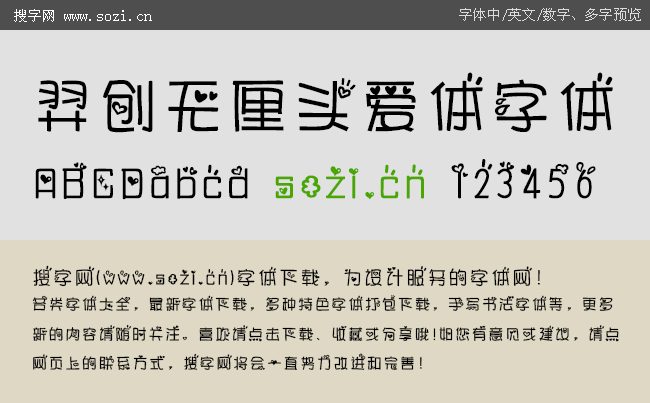
羿創(chuàng)無厘頭愛體字體
搜字網(wǎng)給大家提供一款羿創(chuàng)無厘頭愛體字體手機(jī)中文字體下載。這款手機(jī)字體是以一款POP風(fēng)格的卡通字體為原形,字體間嵌入了可愛的卡通圖案,是非?蓯鄣囊豢钭煮w,特別適合喜歡手機(jī)字體個(gè)性一些的朋友在手機(jī)上安裝使用。